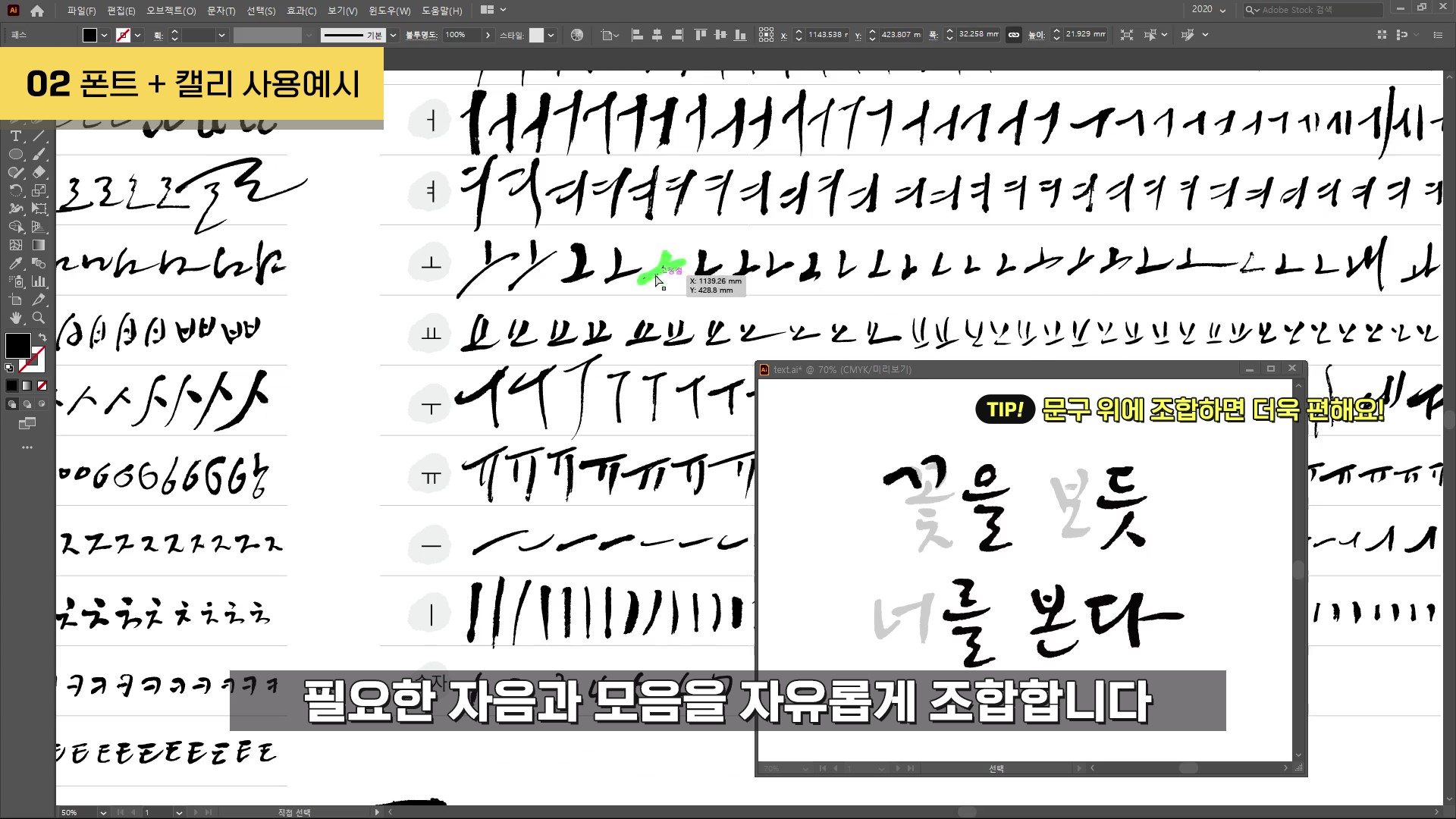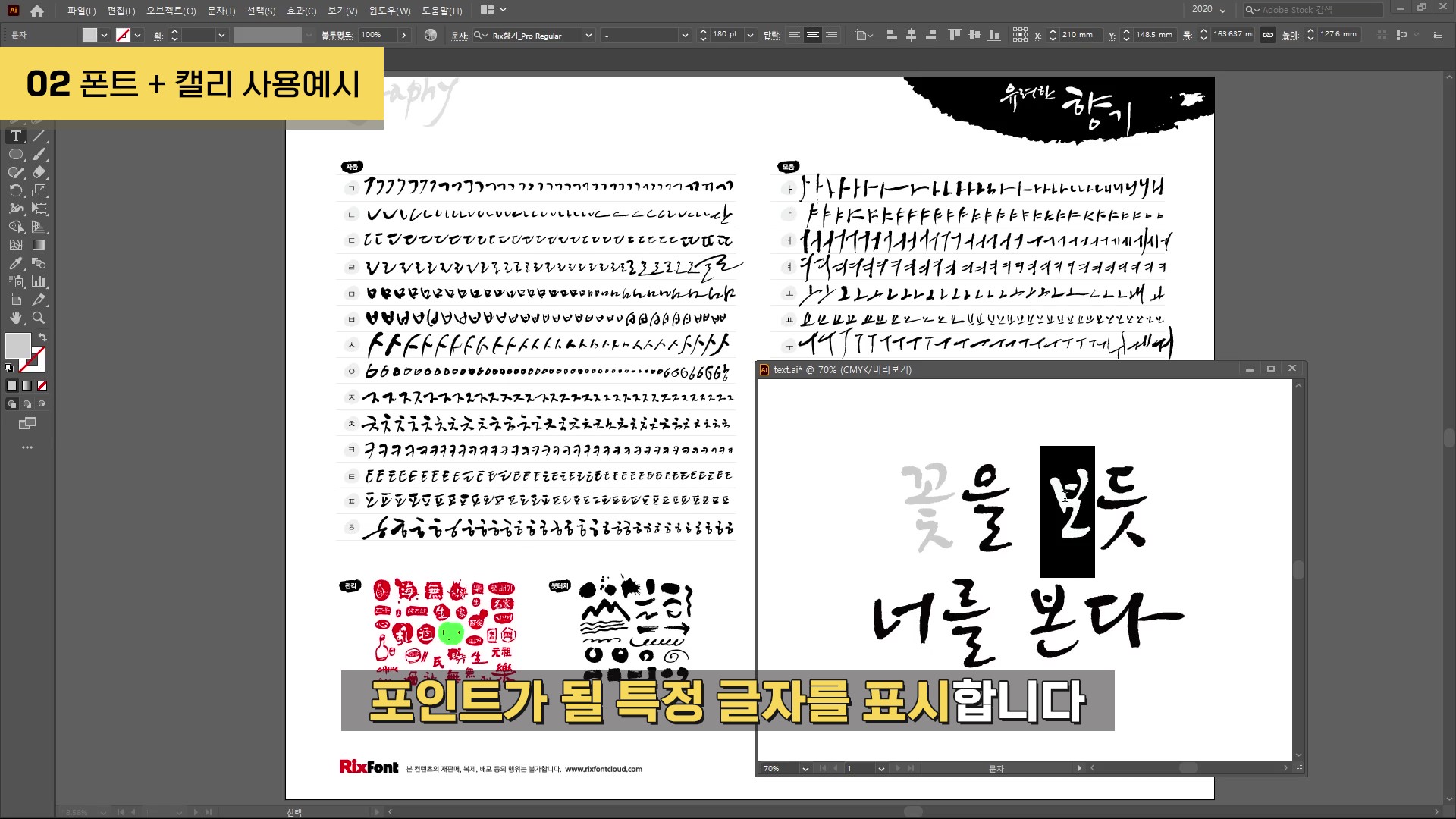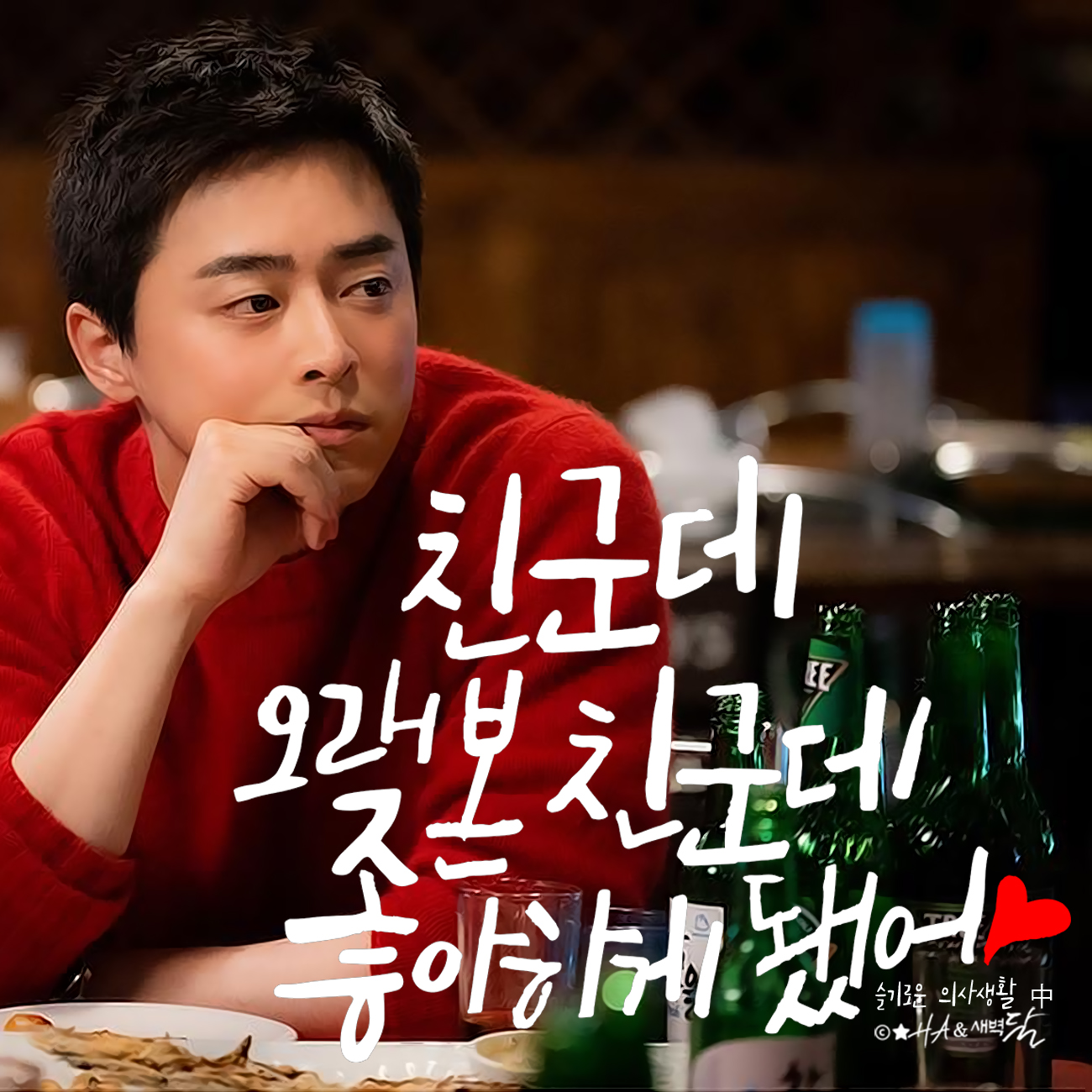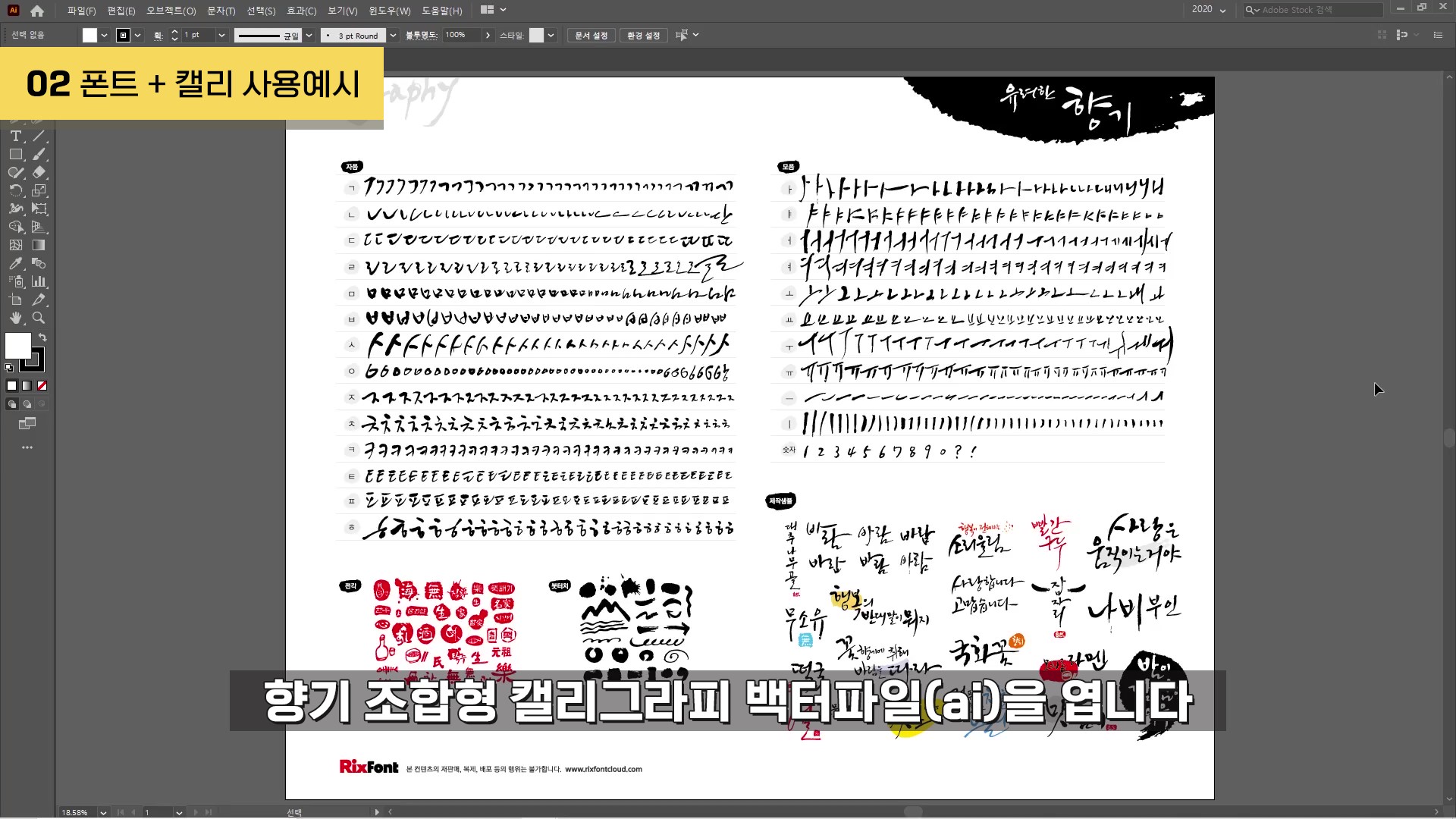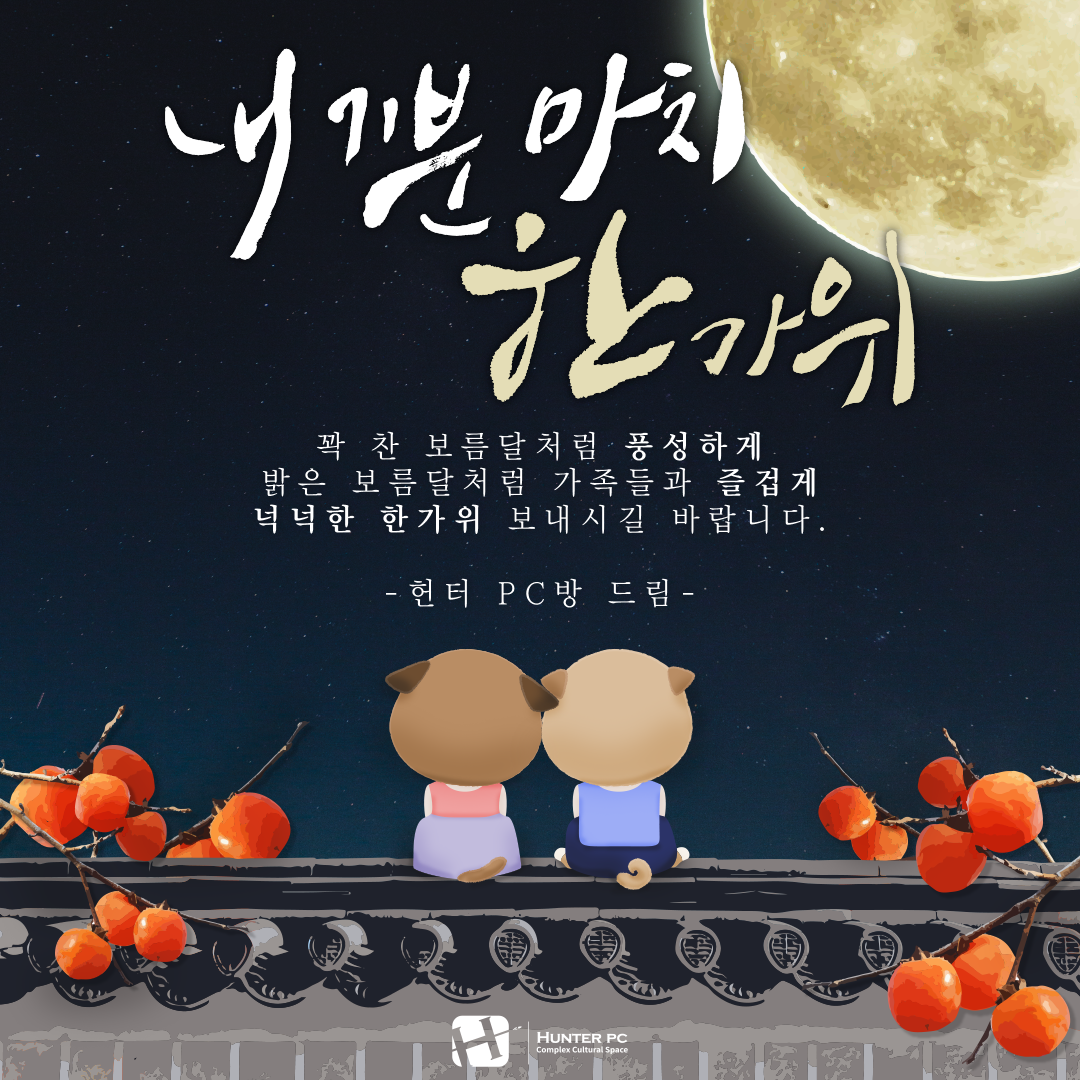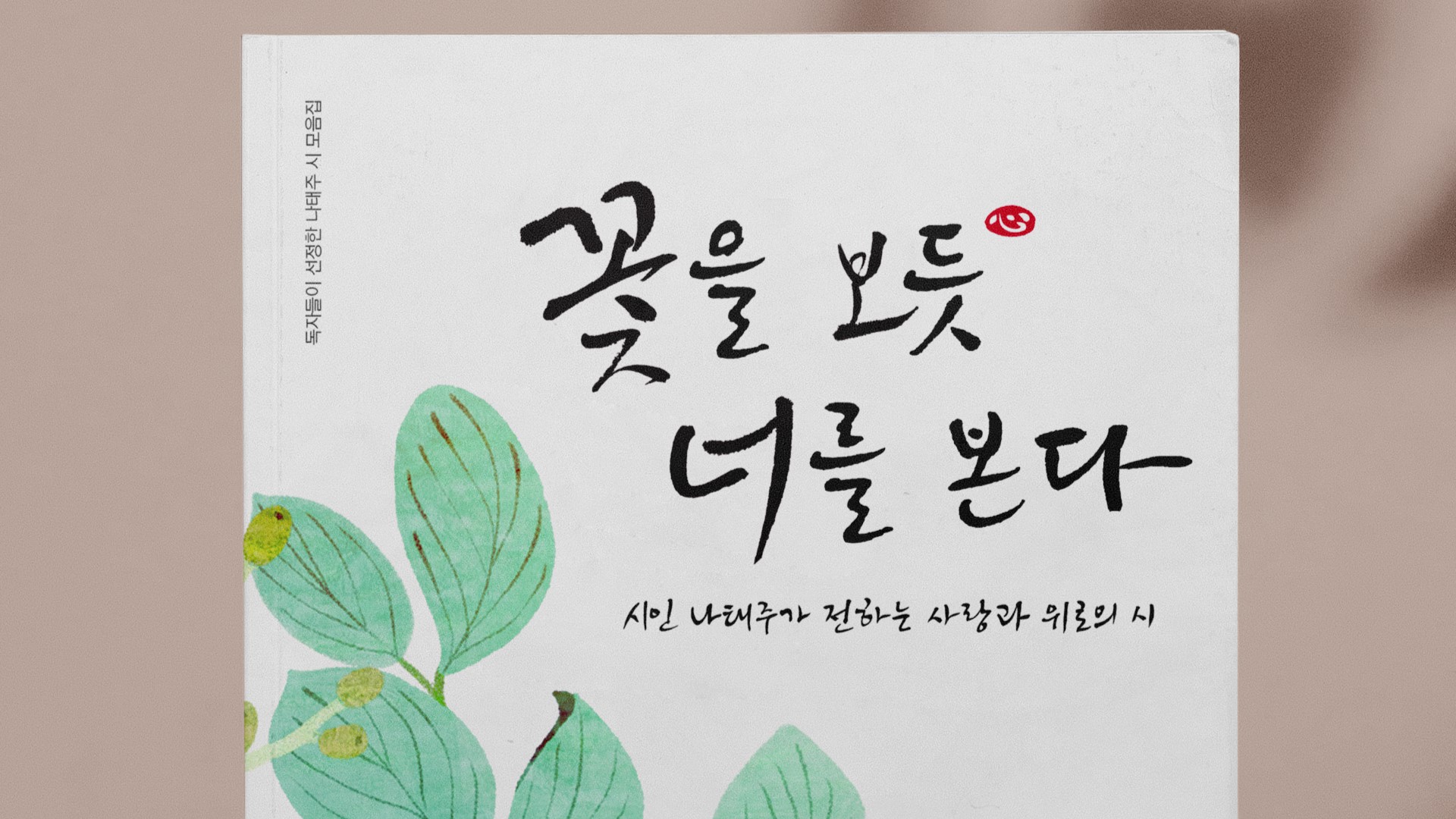
이번에 특별히 폰트와 캘리그라피가 함께 출시된 Rix향기 서체.
쉽고 빠르게 적용할 수 있는 폰트와 다양한 활용이 가능한 캘리그라피를 함께 사용하여 더 멋진 디자인을 만드는 방법을 알려드리려고 합니다. 영상을 보고 아래 자세한 활용법을 따라 순서대로 작업해 보세요!
#1 캘리그라피 파일 불러오기
먼저, ai(벡터이미지)파일로 된 캘리그라피 '향기'를 불러와야겠죠?
아래와 같이 붓글씨 자음/모음 730개+숫자 12개+제작샘플+전각/한자 35개+붓터치 26개의 캘라그라피 구성을 볼 수 있습니다.
*캘리그라피 종류에 따라 구성은 조금씩 다름
#2 폰트로 원하는 문구 쓰기
다음은 새 창을 열어서 향기 '폰트'로 내가 쓰고 싶은 문구를 적습니다.
문구를 먼저 생각해놓고 작업을 해야 훨씬 효율적~!
#3 특정 글자에 표시해주기
그리고 세 번째, 캘리를 활용해 넣고 싶은 특정 글자를 연한 색으로 표시해 줍니다.
#4 문구 위에 조합하기
연하게 표시한 글자 위에 내가 쓰고 싶은 자음 또는 모음을 가져가 얹어봅니다.
비교적 단정한 글줄인 폰트와 조합하면 캘리만으로 하는 조합보다 조금 더 자연스럽게 매치할 수 있고, 망칠 걱정 없이 수월하게 작업할 수 있어요.
#5 일러스트 효과 활용하기
아래와 같이 폰트에는 없는 전각이나 붓터치 등 일러스트적인 효과도 추가할 수 있어 더욱 풍성한 디자인을 만들 수 있답니다.
완성된 글자를 책 표지 디자인에 제목으로 적용해본 모습입니다.
힘 있고 유려한, 먹을 머금은 듯한 글자가 북 디자인의 퀄리티를 한층 높여준 느낌입니다.
볼수록 시와 참 잘 어울리는 'Rix캘리-향기'와 'Rix향기' 폰트의 콜라보!
타이틀은 이렇게 폰트와 캘리를 조합해서 활용하고, 부제는 같은 스타일의 폰트로 문구를 적어 적당한 크기로 넣어주면 책 표지로 손색없는 예쁜 디자인이 완성됩니다.
Rix캘리와 폰트를 사용한 실제 디자인 작업물입니다.
캘리그라피와 폰트를 조합해 타이틀이나 로고, 배너 디자인으로 활용하면 한층 풍성한 느낌을 줄 수 있습니다.